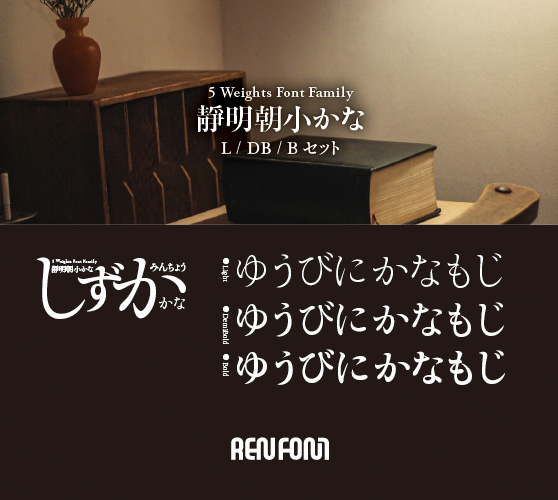
明朝体
靜明朝小かな-中・小見出し用3ウェイトセット(L/DB/B)
「小説などの長文を組んでもらいたい」とのコンセプトをもとに開発しました。靜明朝には「大かな」と「小かな」があり、このフォントは縦組みに適した「小かな」です。縦組みの長文に使ってみてください。落ち着いた、それでいながら訴求力のある紙面になるはずです。縦組み、横組みともプロポーショナル加工を加えました。また、ペアカーニングも緻密にほどこしてあります。中・小見出し用3ウェイトセット。